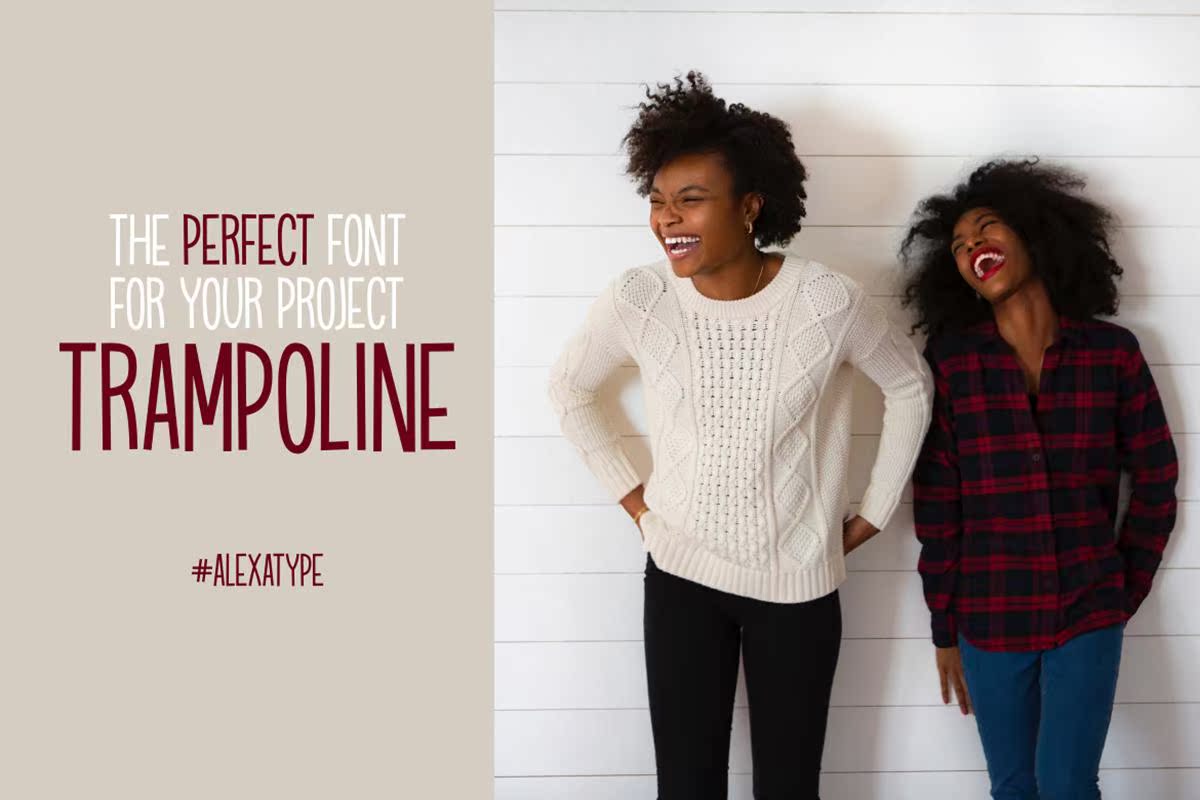
FreeDemoRampolinesansserieffort用于测试版本转换,采用通用样式作为灵感来源。它适用于您的项目,包括用于编辑、包装设计和网站的前端字体。它包括大小写,显示超过100个唯一字符、数字。此自由字体使用格式文件进行编码,尝试不安装任何设备。但是,如果是个人使用,请购买PremiumVersion以获得更多功能。